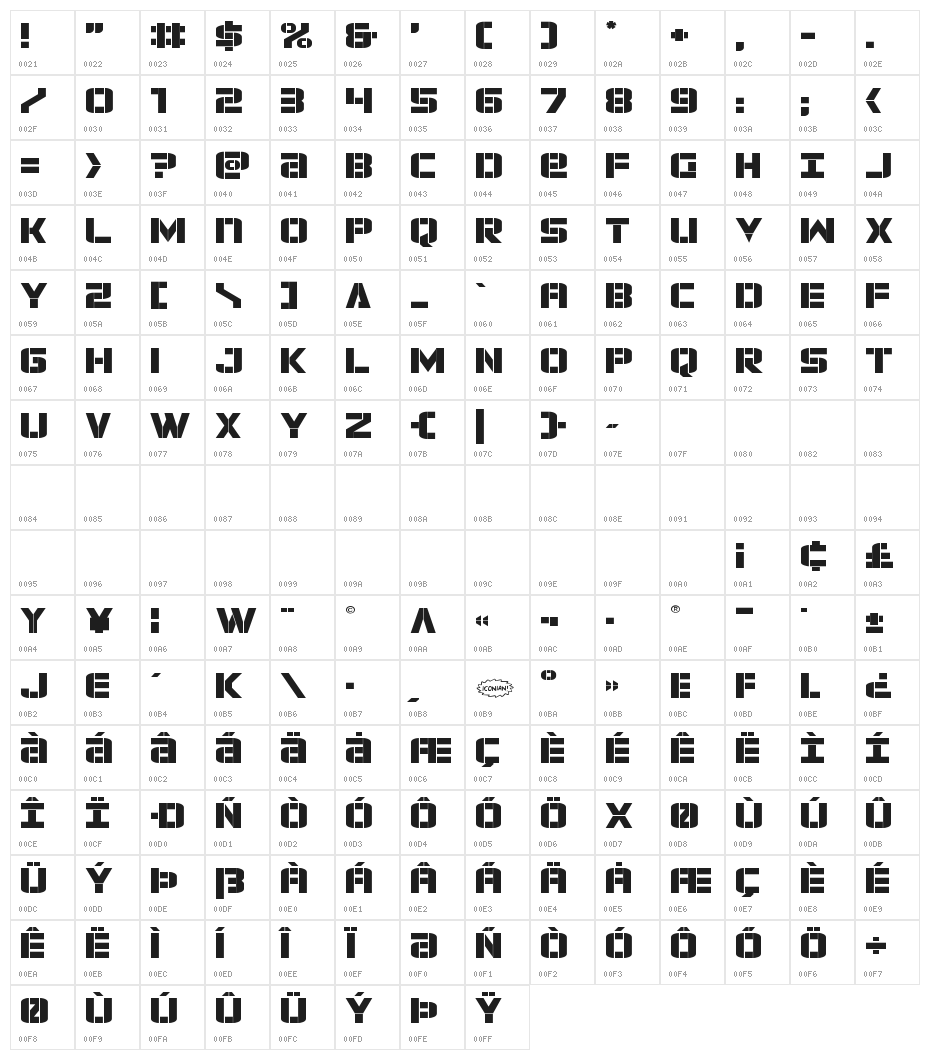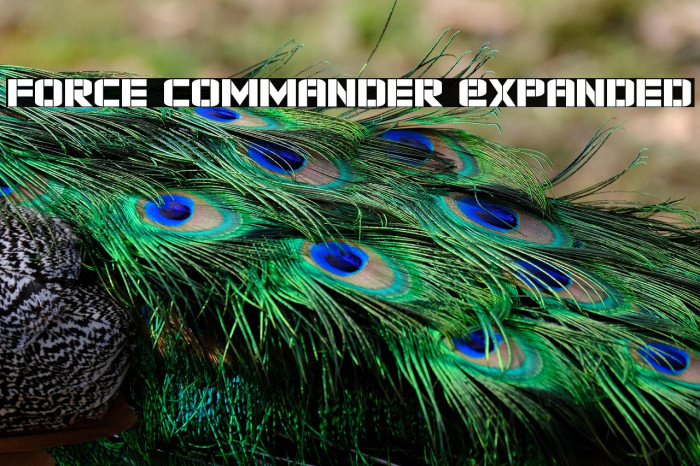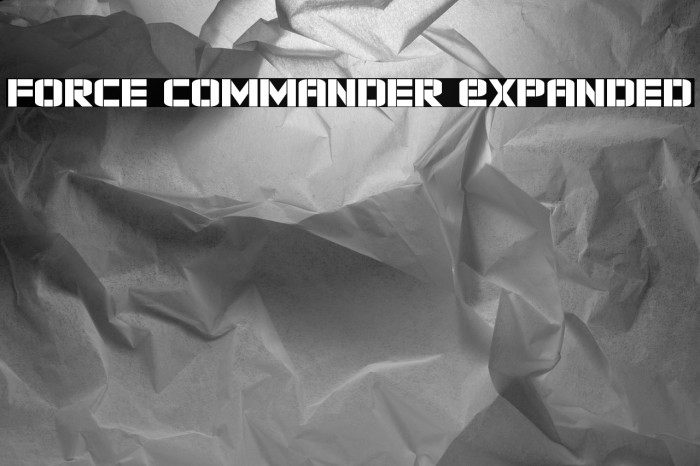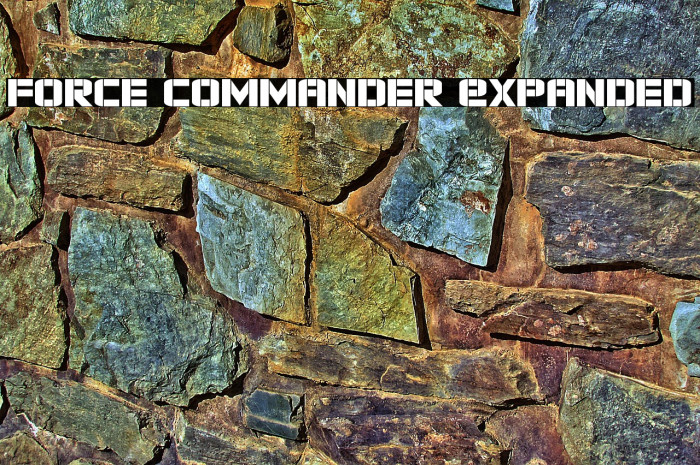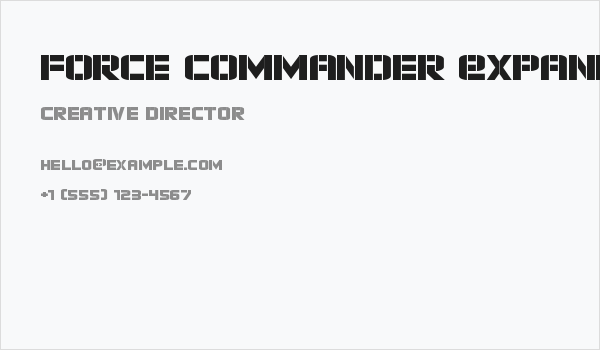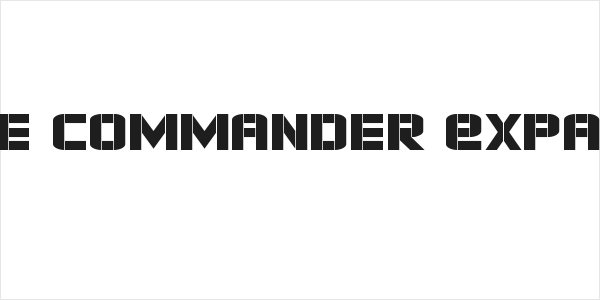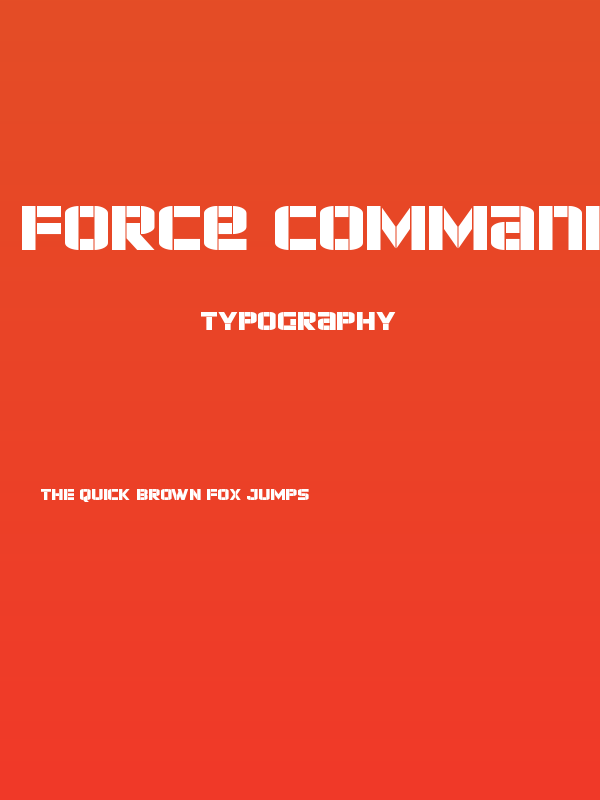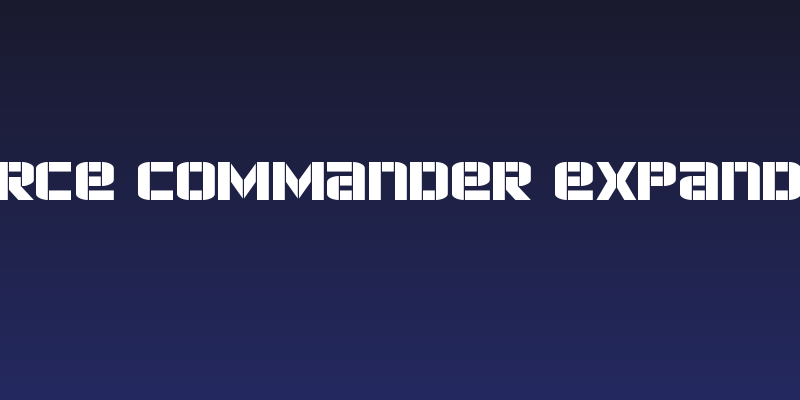
Force Commander Expanded Font
| おすすめプロジェクト | Ideal for technology branding, video game titles, sci-fi movie posters, and industrial-themed designs. |